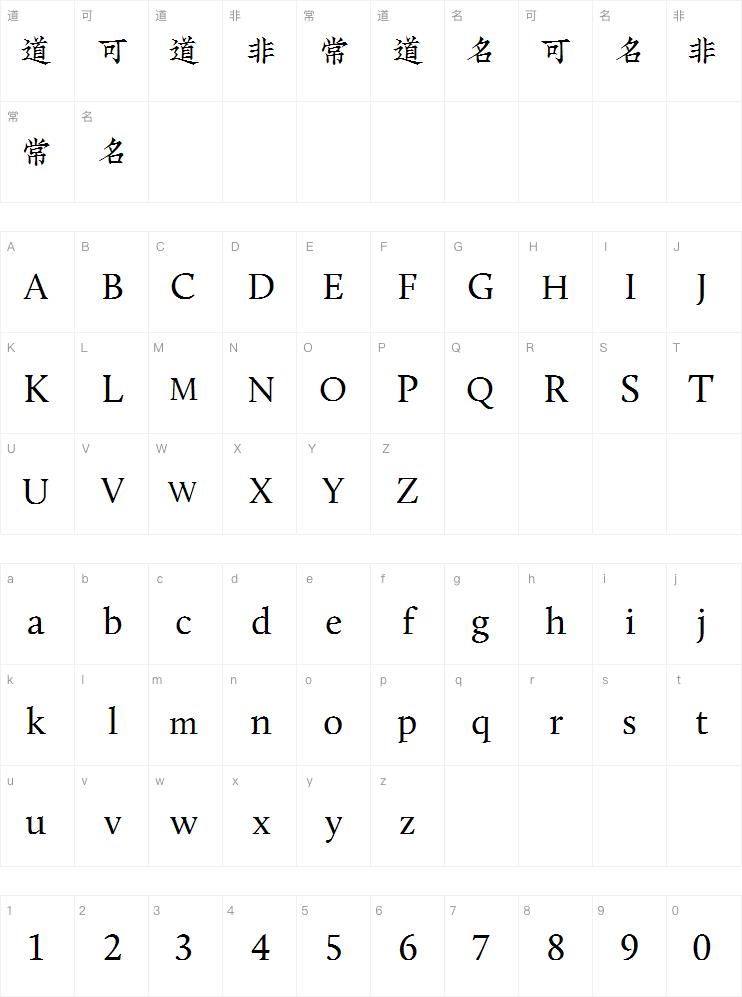
字悦聚珍仿宋源自清末至中华民国初年的活字“聚珍仿宋”。当时丁善之、丁辅之等人不满市面上普遍使用的由日本输入的宋体活字字型,于是参考刻印史上最为适观的北宋刊本中的字型,设计了 “聚珍仿宋” 活字字体,字悦聚珍仿宋则是在此基础上进行复刻和优化,在老字形基础上设计为现代规范字形,并扩展至繁简通用字,达到GBK万级字数量标准,以及更适合在计算机上应用。